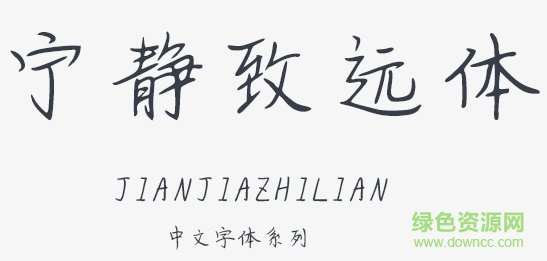
寧靜致遠(yuǎn)體是一款字跡清秀雋永的手寫字體,文字利落而流暢,給人十分舒適的視覺體驗,讓你的文字設(shè)計更加打動人心,快來綠色資源網(wǎng)試試吧!
寧靜致遠(yuǎn)意思是只有心境平穩(wěn)沉著、專心致志,才能厚積薄發(fā)、有所作為。
寧靜致遠(yuǎn)體就能給人一種淡迫名利的自在感,閱讀閑適干凈自然。
寧靜致遠(yuǎn)字體有著輕松悠閑的外觀,結(jié)構(gòu)疏松而大方端正,無過多的筆觸和收尾,讓文字呈現(xiàn)一股清新優(yōu)雅的外在美,給你的藝術(shù)設(shè)計、海報設(shè)計、平面設(shè)計、包裝設(shè)計等帶來獨特呈現(xiàn)!